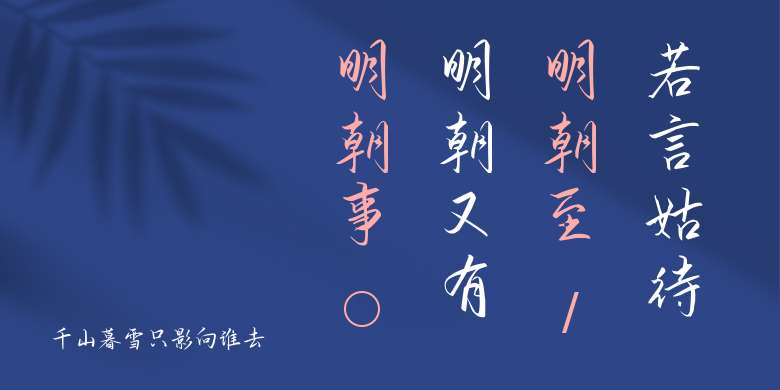
千山暮雪只影向谁去
千山暮雪只影向谁去,这款字体结构工整、笔画清晰,兼顾美观与易读性,适用于标题、正文、海报、包装、LOGO 等多种场景。字形优雅稳定,风格百搭耐看,适配日常排版与创意设计,让文字呈现更舒适、更具质感。千山暮雪只影向谁去一笔一画,皆是细节,以均衡的比例、流畅的线条打造舒适视觉体验,字形端正大气,风格简约现代。无论是商业设计、品牌宣传还是日常排版,都能轻松驾驭,让文字更有格调与力量。千山暮雪只影向谁去字体下载。